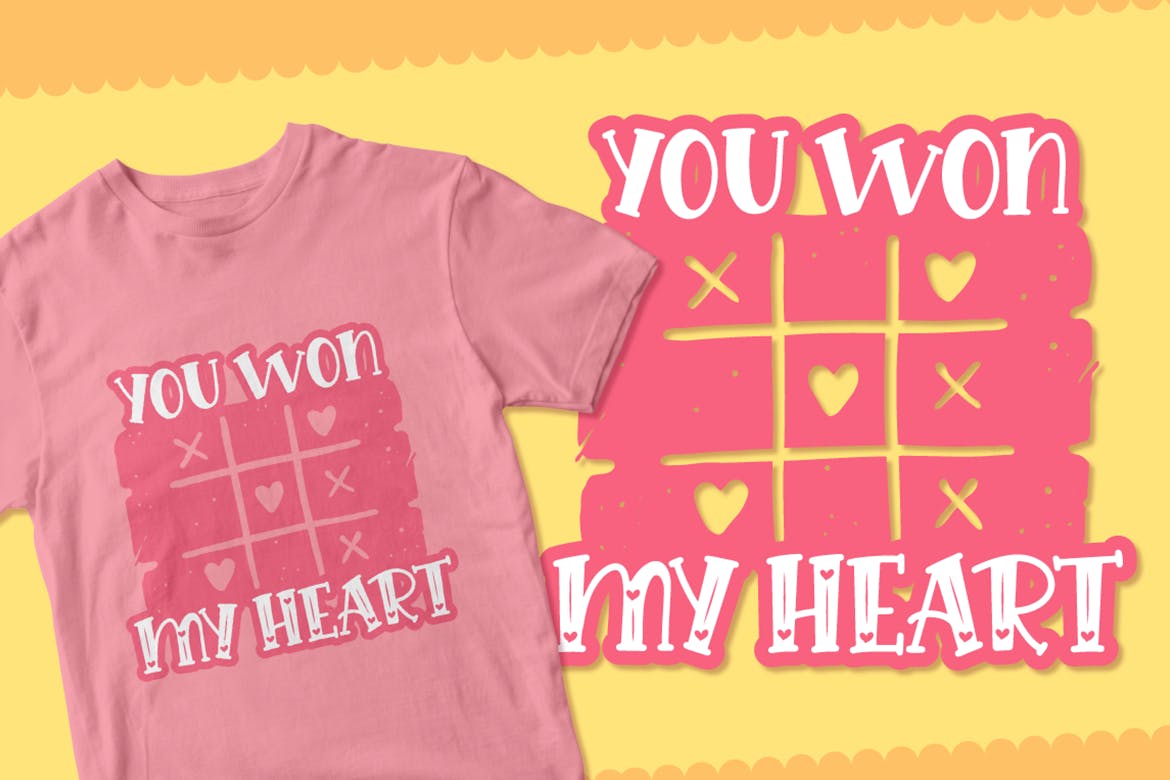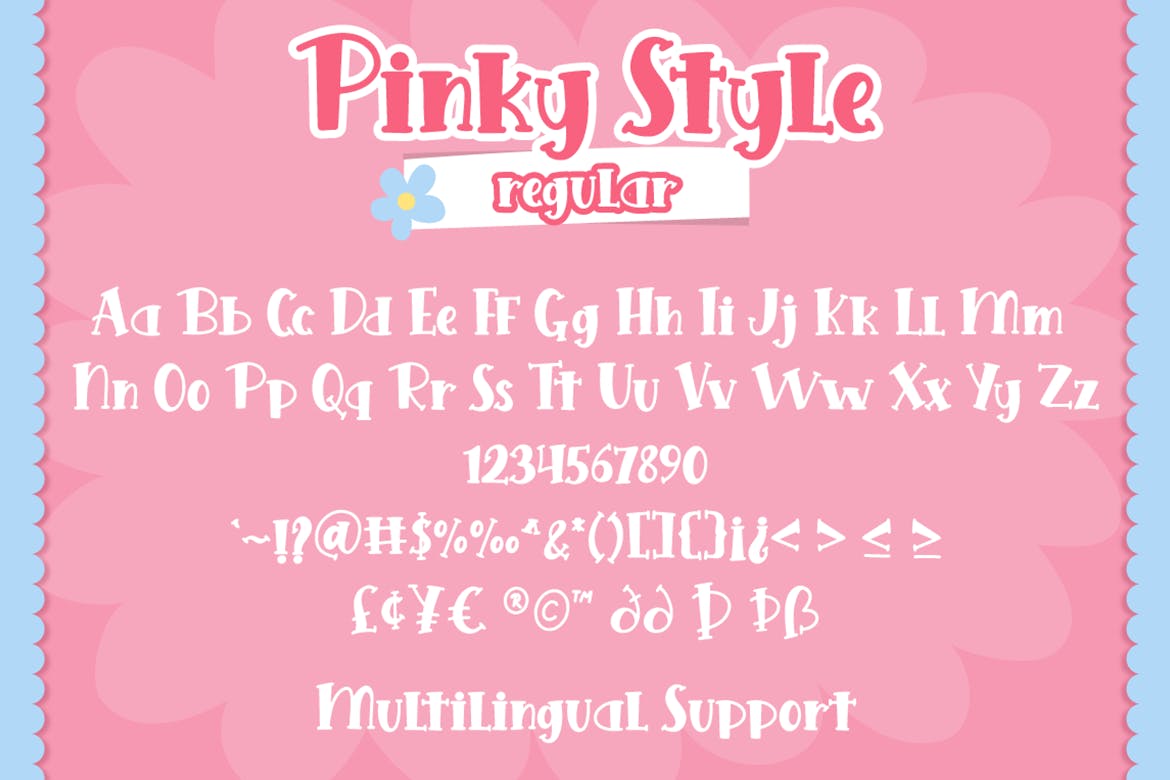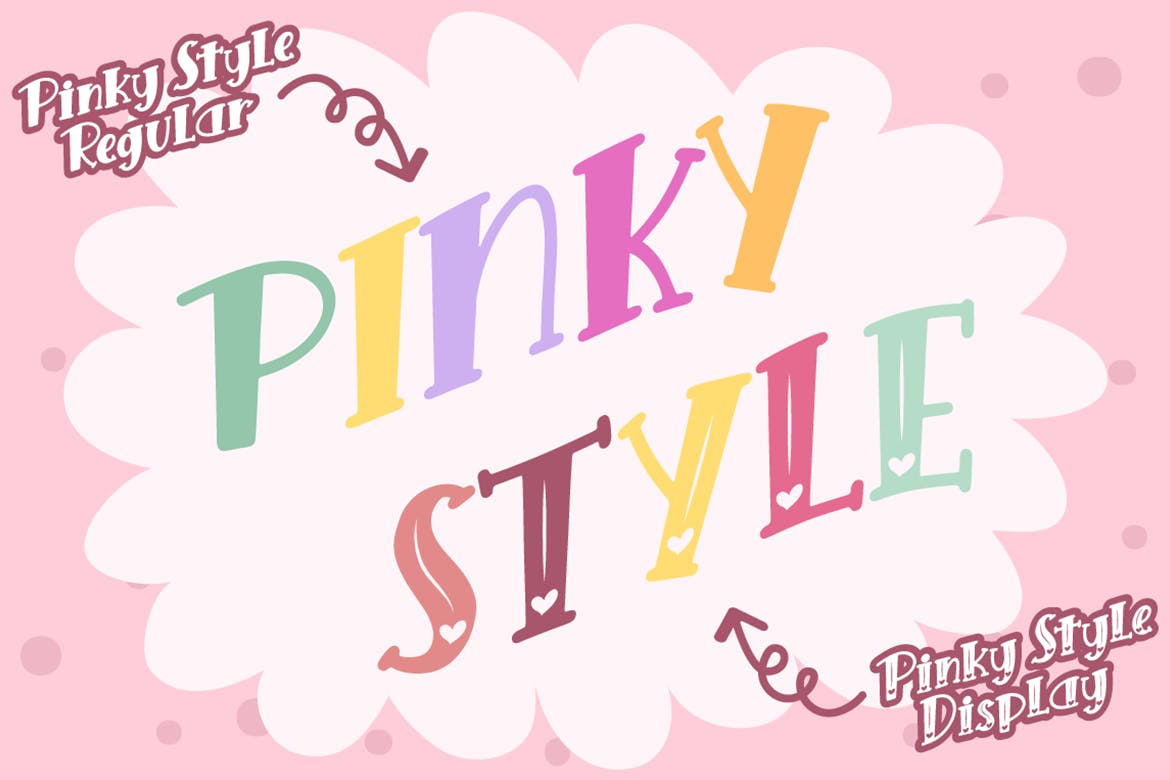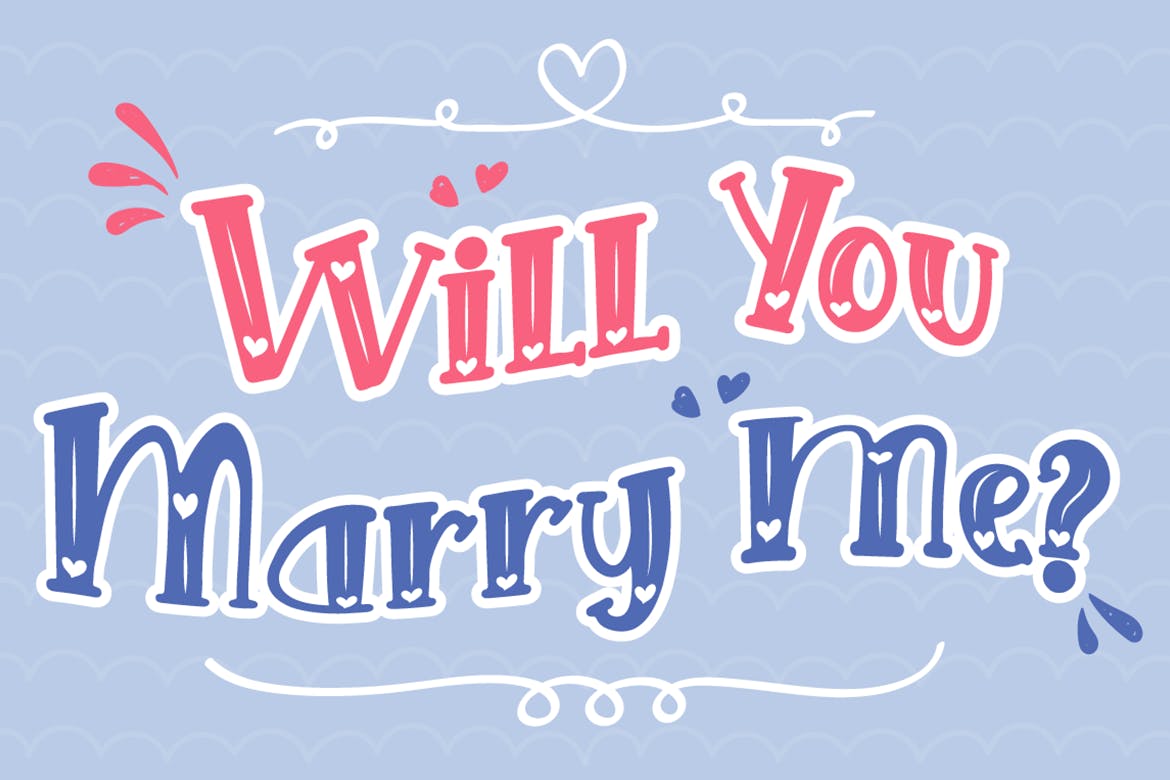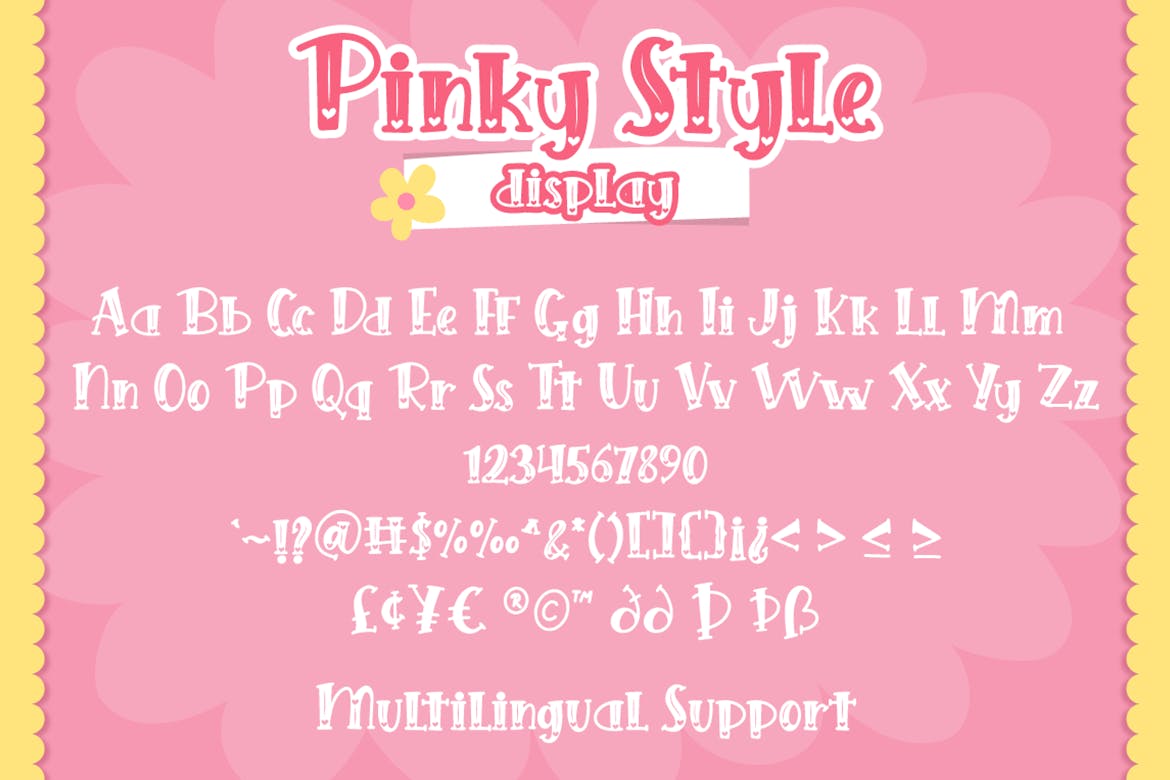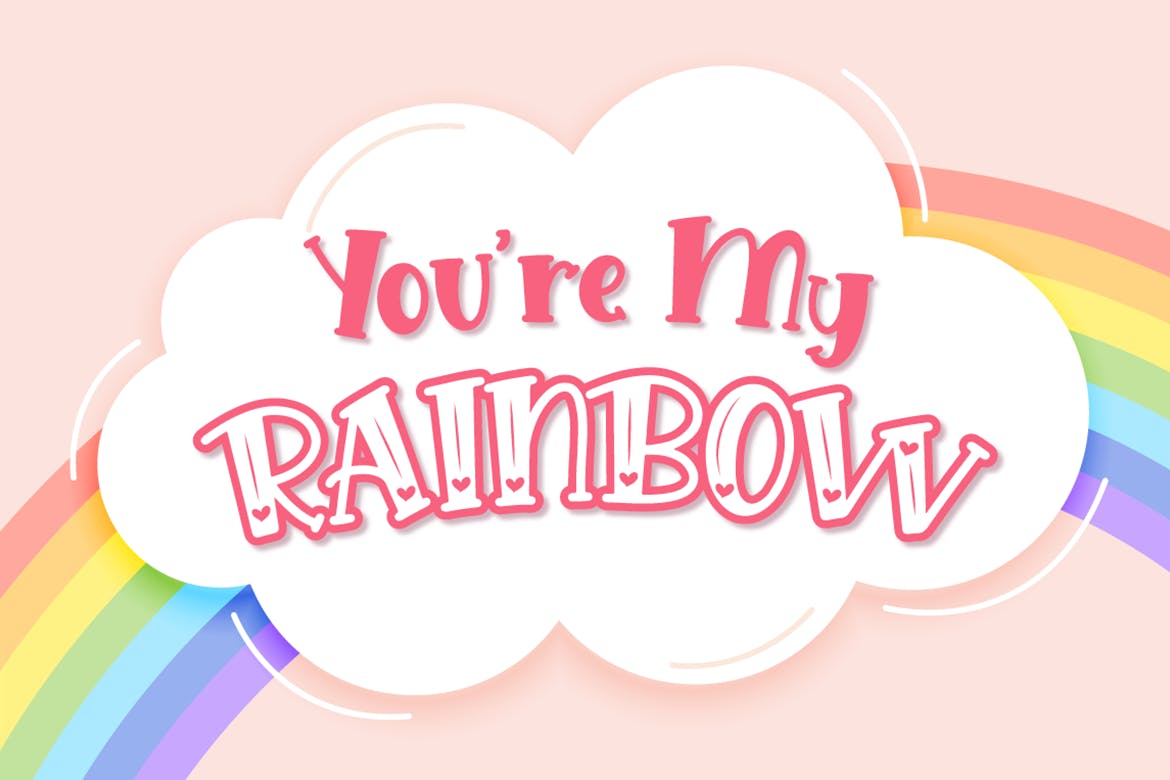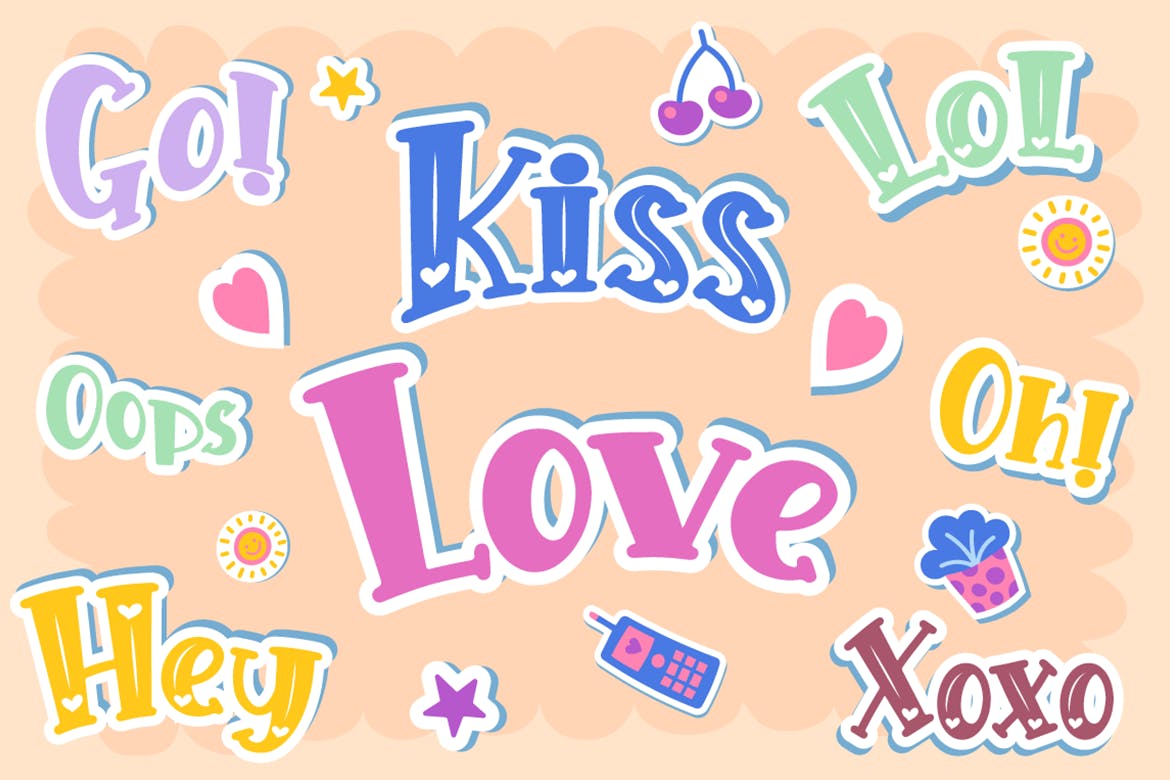
Pinky Style Lovely Craft Font
با فونت Pinky Style طراحی‌های عاشقانه و منحصر به فرد خود را خلق کنید.
Pinky Style یک فونت نمایشی زیبا و عاشقانه با طراحی قلب است. با سبک فوق‌العاده متنوع آن عاشق شوید و از آن برای ایجاد طراحی‌های دیدنی استفاده کنید!
Pinky Style برای برندینگ، لوگو، دعوتنامه‌ها، نقل قول‌ها، طراحی پوشاک، بسته‌بندی محصولات، کالاهای تجاری، عناوین بازی، طراحی‌های بامزه، عنوان کتاب و موارد دیگر کاملاً مناسب است.
• پشتیبانی چندزبانه